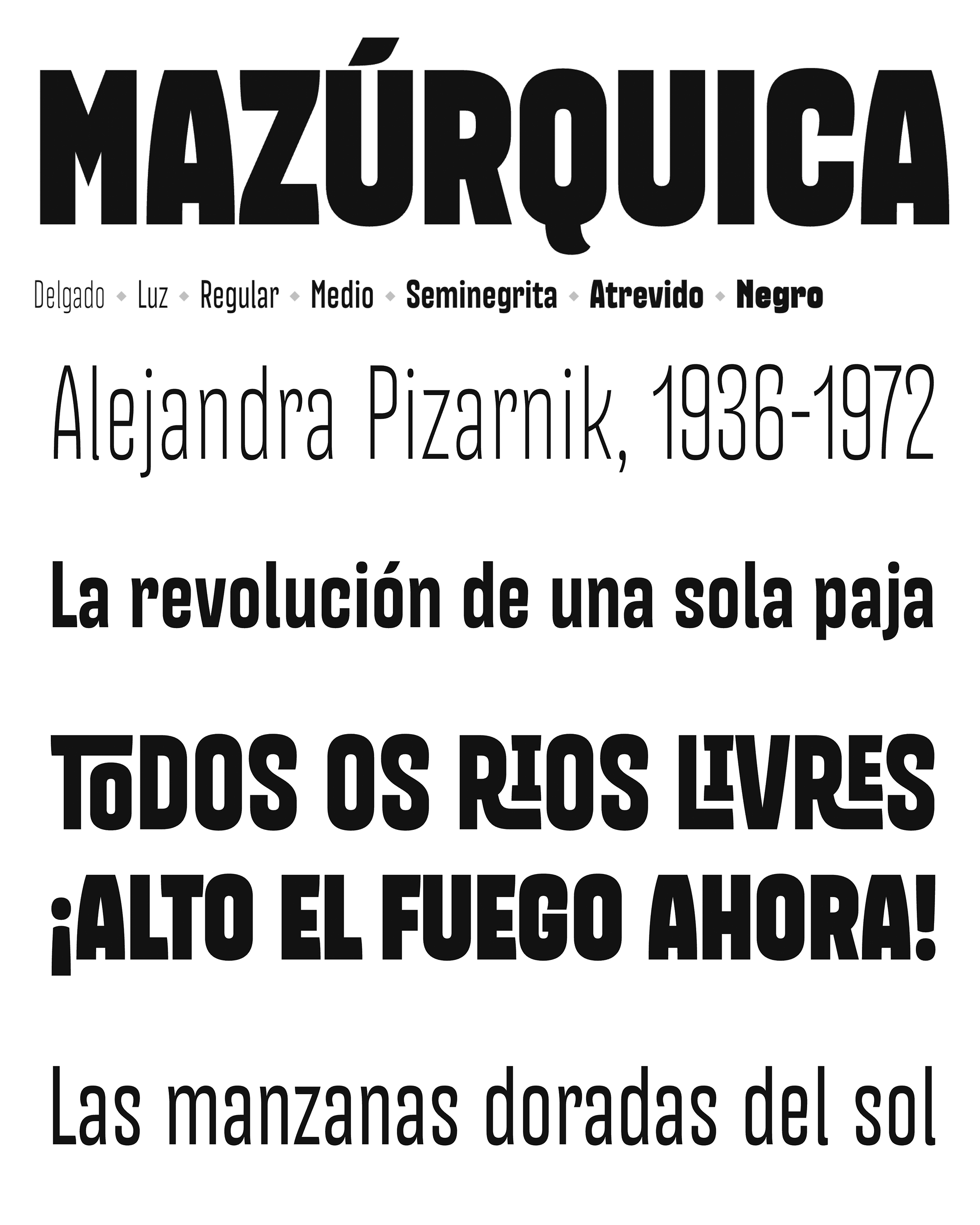
| Año | 2020 |
| Créditos | Guido Ferreira, Javier Quintana |
| Descripción | Mazúrquica es una tipografía grotesca condensada que combina algunos aspectos de la xilografía del siglo XIX con un sutil contraste inverso y formas que recuerdan algunos aspectos formales de las letras callejeras de Santiago y Valparaíso. Su particular estética y estructura condensada la convierten en una tipografía ideal para componer titulares impactantes y textos breves. Es ideal para diseño editorial, logotipos, motion graphics y cualquier contexto donde se necesite transmitir un mensaje claro y contundente. |
| Fundidora | Quintana fonts |